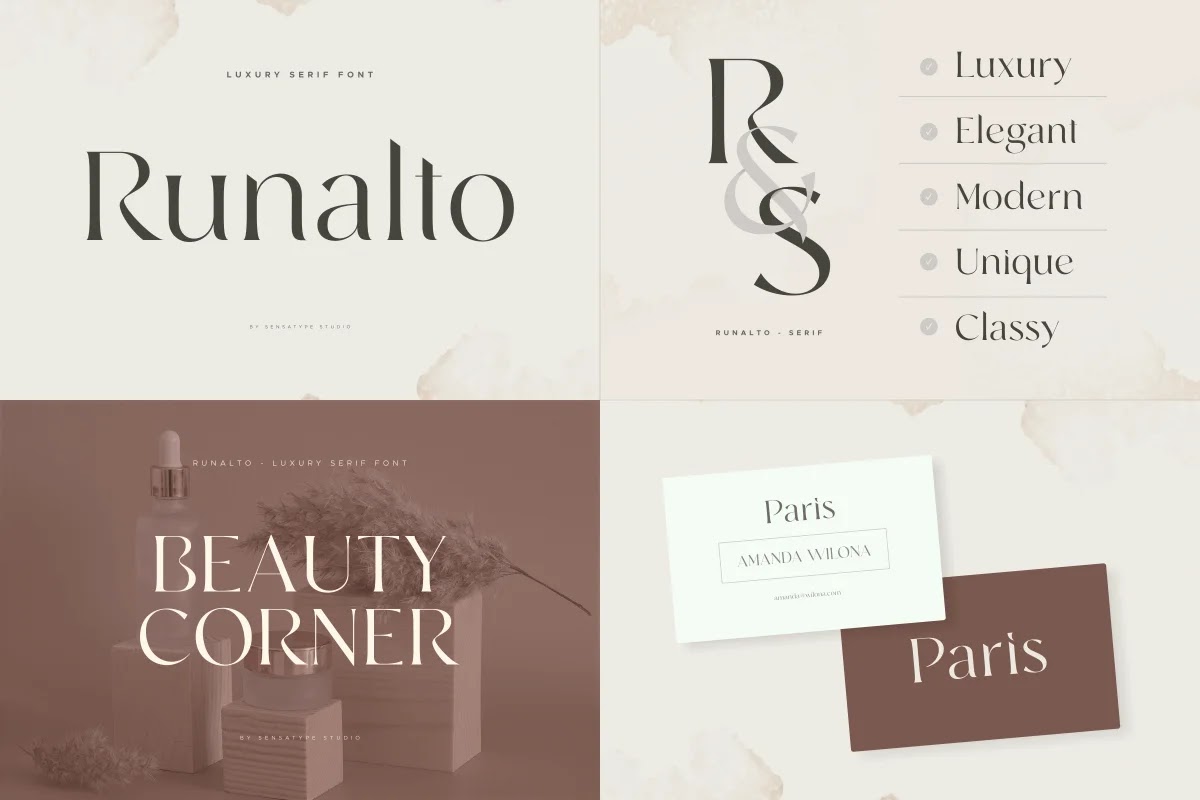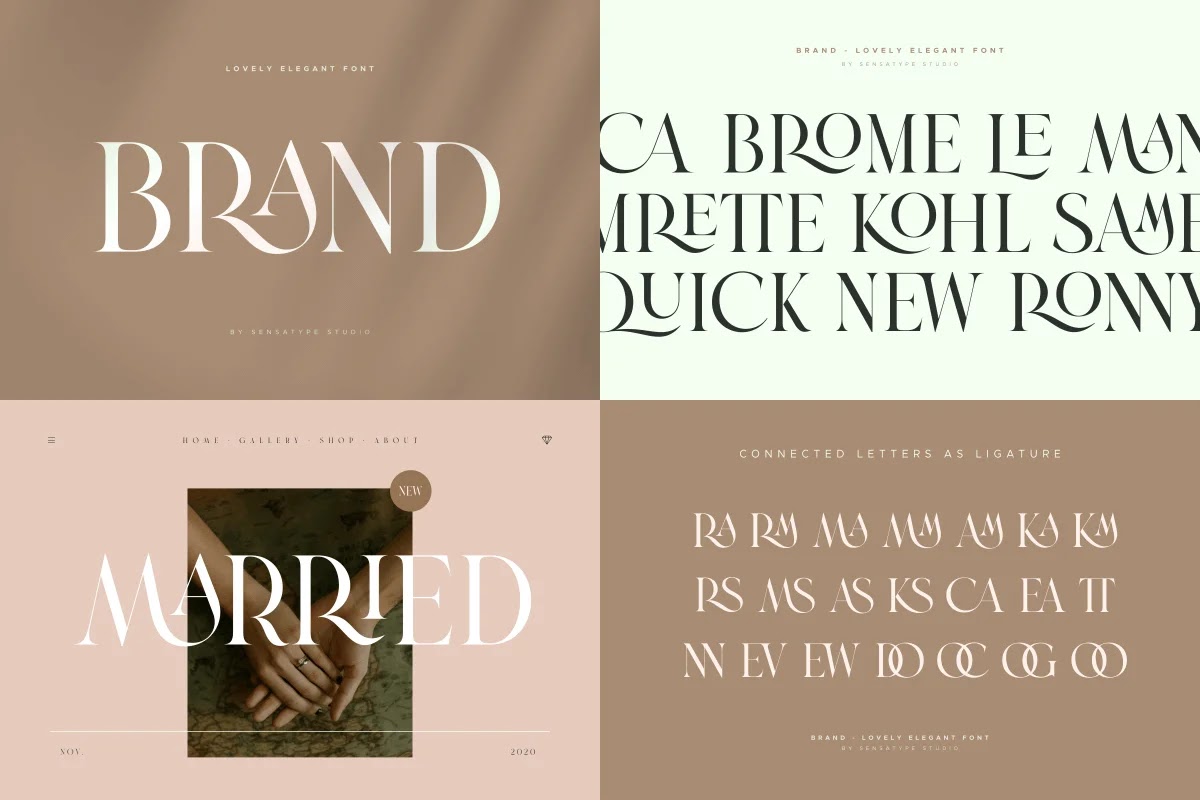
Tải ngay 11 font chữ tuyệt đẹp sưu tầm trên Creativemarket
Unique and Classy Modern Font Bundle 5961991 - Bao gồm 11 font trả phí tuyệt đẹp được sưu tầm trên Creativemarket. Đây là một bọ font chữ độc đáo để làm cho ý tưởng trở nên sẵn sàng để sử dụng một cách dễ dàng. Điều này là hoàn hảo cho THƯƠNG HIỆU và THIẾT KẾ LOGO. Bạn sẽ có được vẻ đẹp độc đáo, sang trọng, thanh lịch và chắc chắn để làm cho các dự án thiết kế hoặc thương hiệu của bạn trở nên nổi bật hơn với font chữ này.